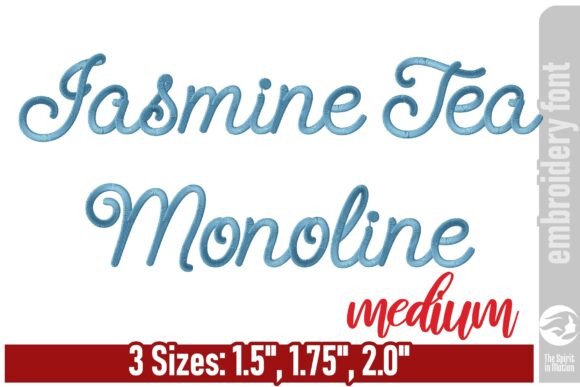
Jasmine Tea Monoline Embroidery Font - M
Пошук відповідних елементів дизайну може бути складним, але Jasmine Tea Monoline Embroidery Font - M пропонує виняткову колекцію, яка миттєво покращить вашу роботу.
Створений з високою точністю, Jasmine Tea Monoline Embroidery Font - M забезпечує чисті вектори, плавну типографіку та комерційну ліцензію для вашого спокою.
Незалежно від того, чи створюєте ви продукти POD (друк на вимогу), весільні запрошення або графіку для соціальних мереж, Jasmine Tea Monoline Embroidery Font - M стане ідеальним вибором.